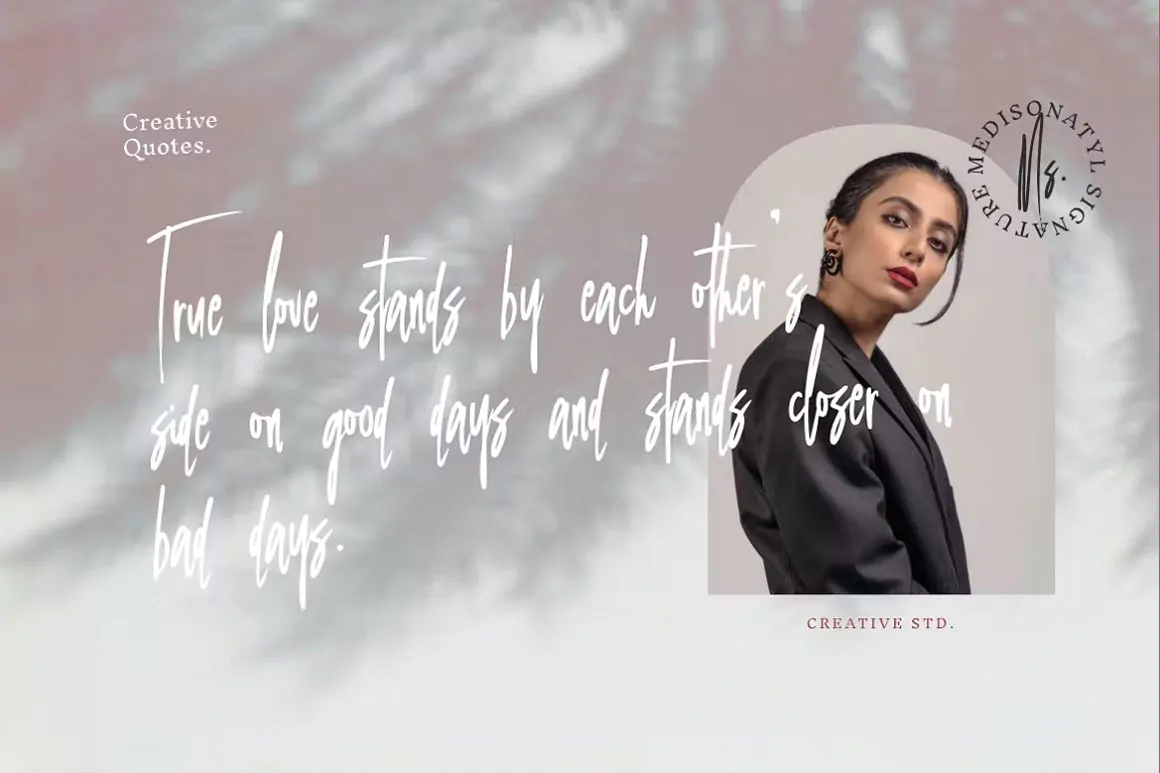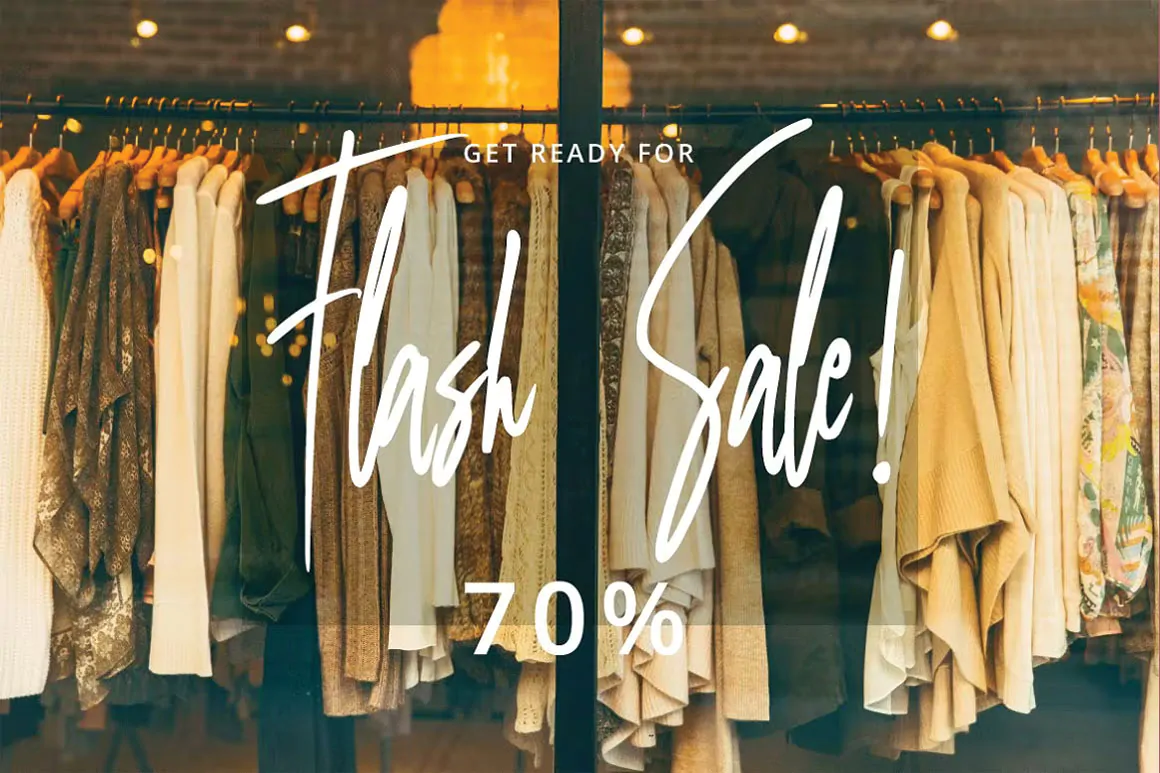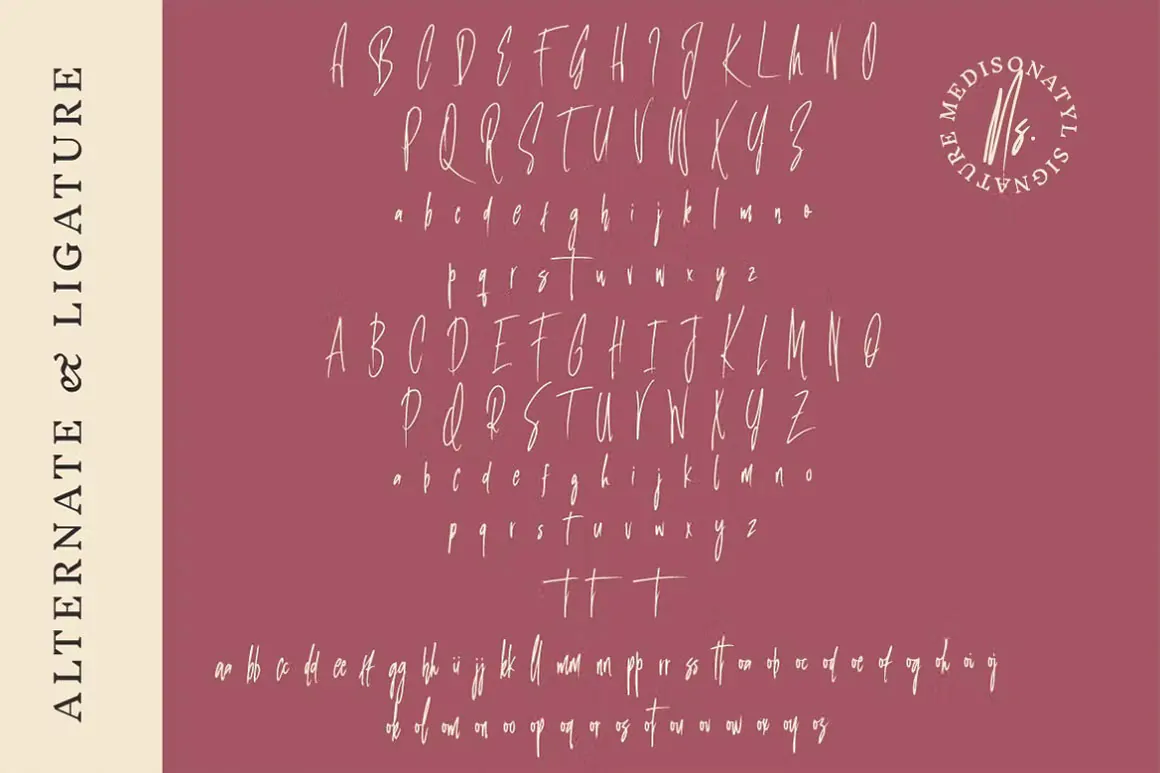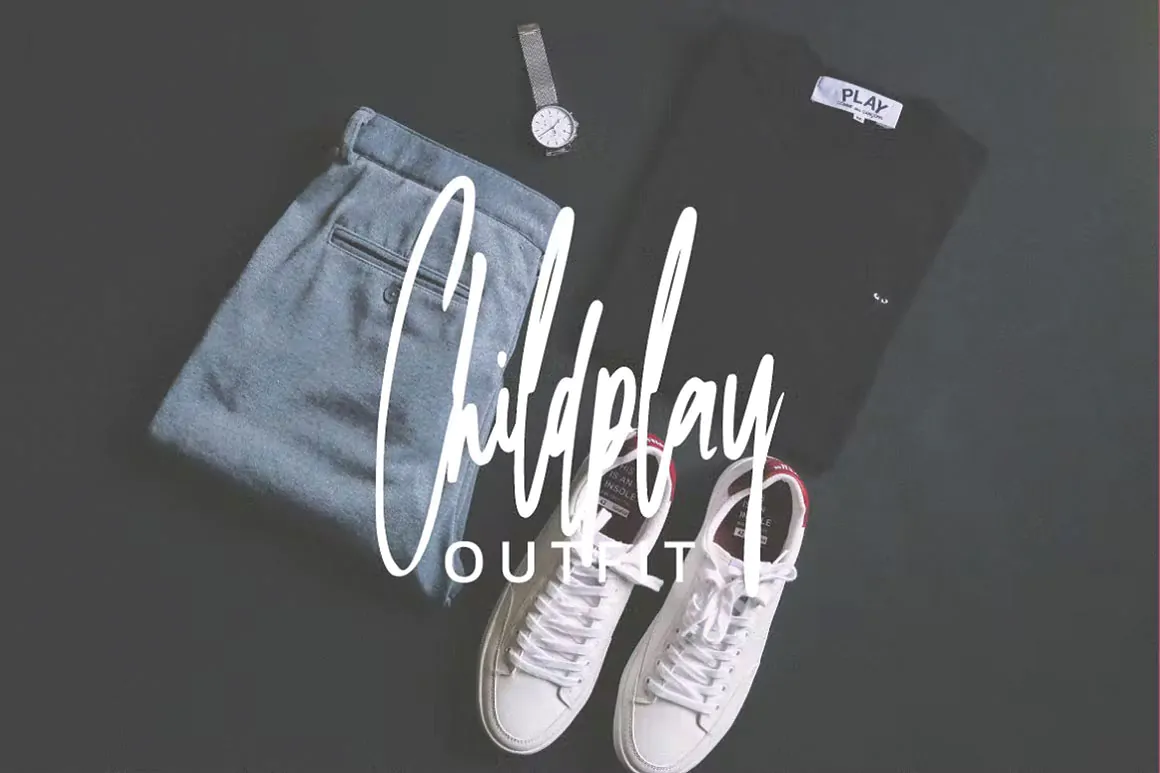
فونت دستنویس سبک امضا Medisonatyl
فونت دستنویس سبک امضا انگلیسی
فونت دستنویس سبک امضا Medisonatyl یک اسکریپت فونت انگلیسی فوق العاده زیبا است که مناسب برای استفاده در طرح و پروژههای گرافیکی مختلف همچون طراحی انواع کارت تبریک، کارت ویزیت، جلد کاور آلبوم موسیقی، بسته بندی محصولات، پوستر، لوازم التحریر، آرایشی و بهداشتی و … میباشد.